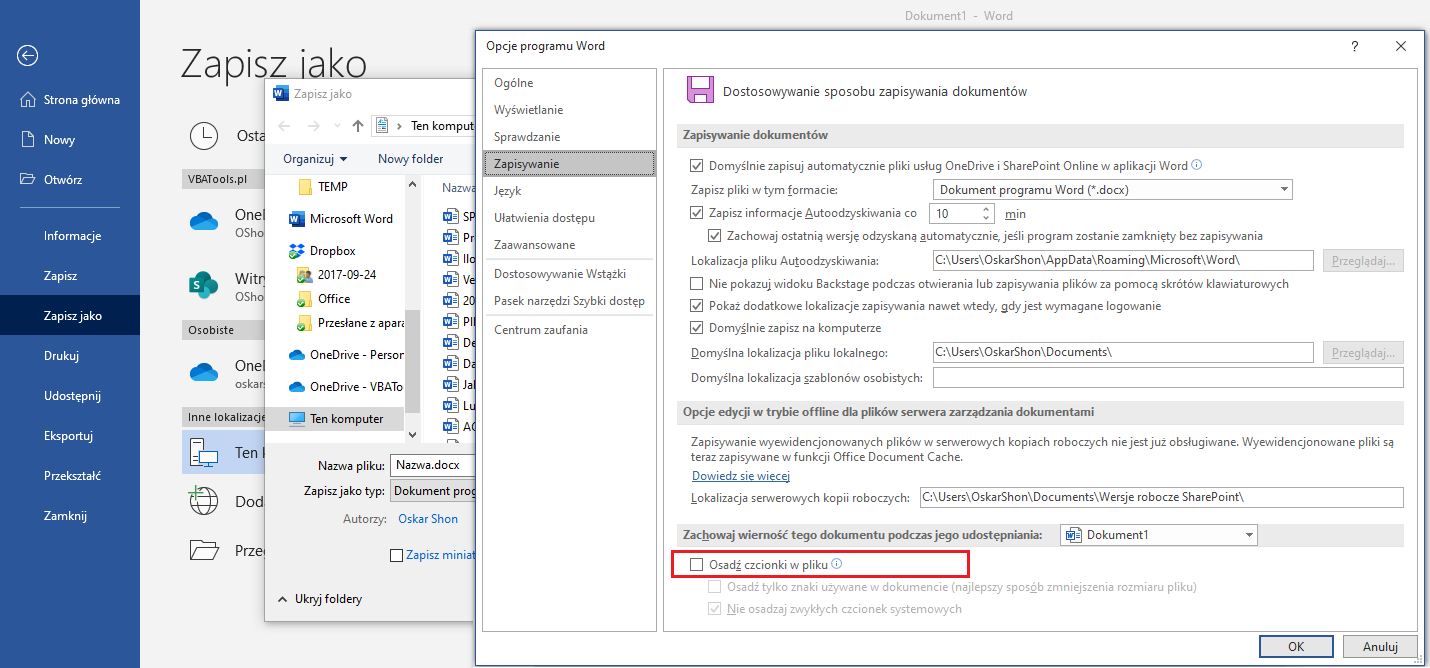
Czcionki w Word
Mam tylko krótkie pytanie. Jakie czcionki były w starszych edytorach i nowszych? Nazwa i rozmiar. Pamiętam, że "nowy Roman" jako podstawowa ale do naglówków nie pamiętam. I w nowszych też chciałbym wiedzieć. Dziękuję z góry za pomoc.
Wybór czcionki najlepiej standardowy, ponieważ może przy starszych komputerach, migracji etc i nie zachowaniu stylu czcionki w dokumencie (mówimy o Wordzie gdzie jest taka możliwość) dojść do transformacji na inną.
Obecnie jest to Calibri a ja lubię bardzo Tahoma ale każda czcionka jest stylizowana nie tylko na czytelność ale na charakter tekstu.
Ciężko pisać o westernach lub rycerzach bez czcionki charakterystycznej dla tego stylu.
Nie ma więc jednej słusznej, najodpowiedniejszej i uniwersalnej.
Oczywiście, ale każdy inny OS od MS wyświetla czcionki idealne, a Windowsa nie mogę się doczytać. Chciałbym uzyskać takie efekty, jakie mam pod Linux Mint. Wygładzanie czcionek tam jest extra!
A jak czcionka, Pana zdaniem, prezentuje się najlepiej pod Windows?
A co to ma za znaczenie. Fakt domyślne czcionki się zmieniły (najwidoczniej ktoś uznał że na monitorach LCD lepiej je odczytać), ale stare czcionki pozostały. Otwarcie starszych plików zapisuje rodzaj czcionki a wiec nie powinno to mieć jakąkolwiek różnice.